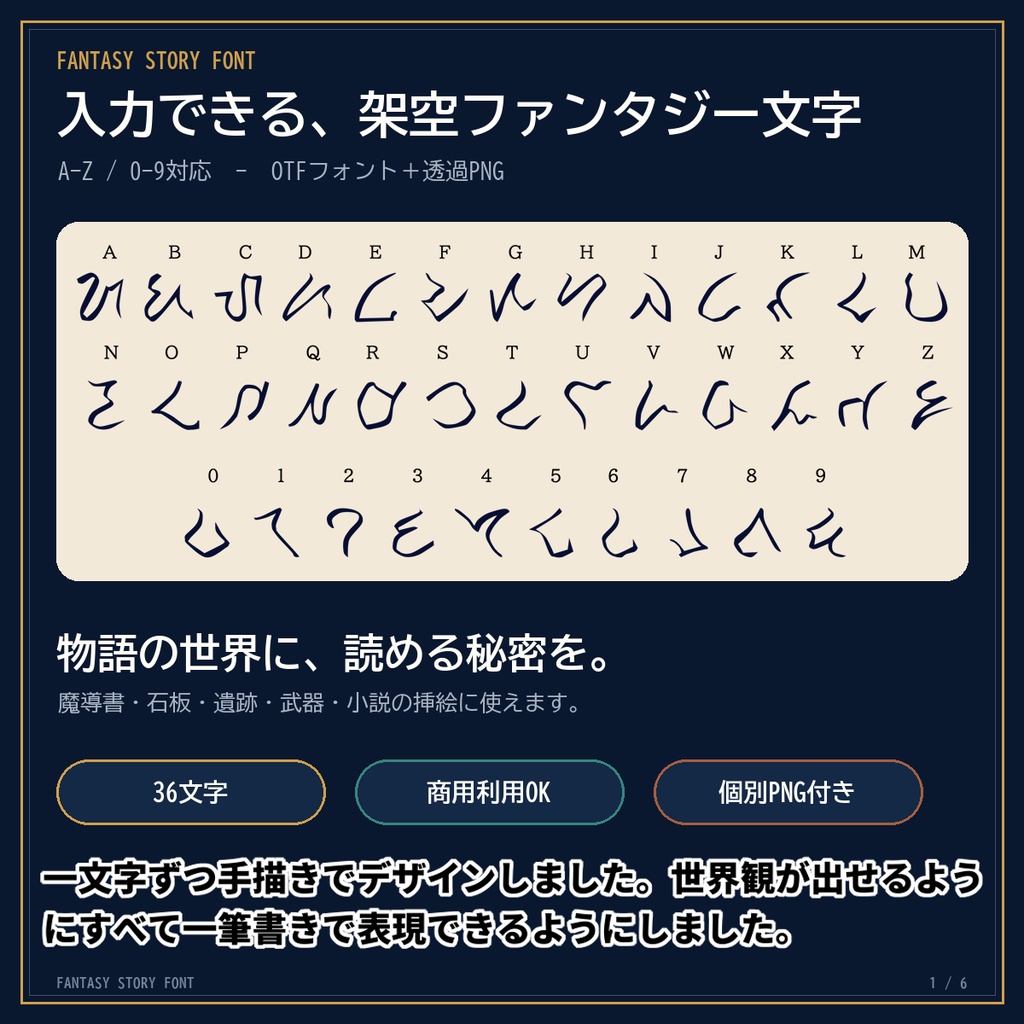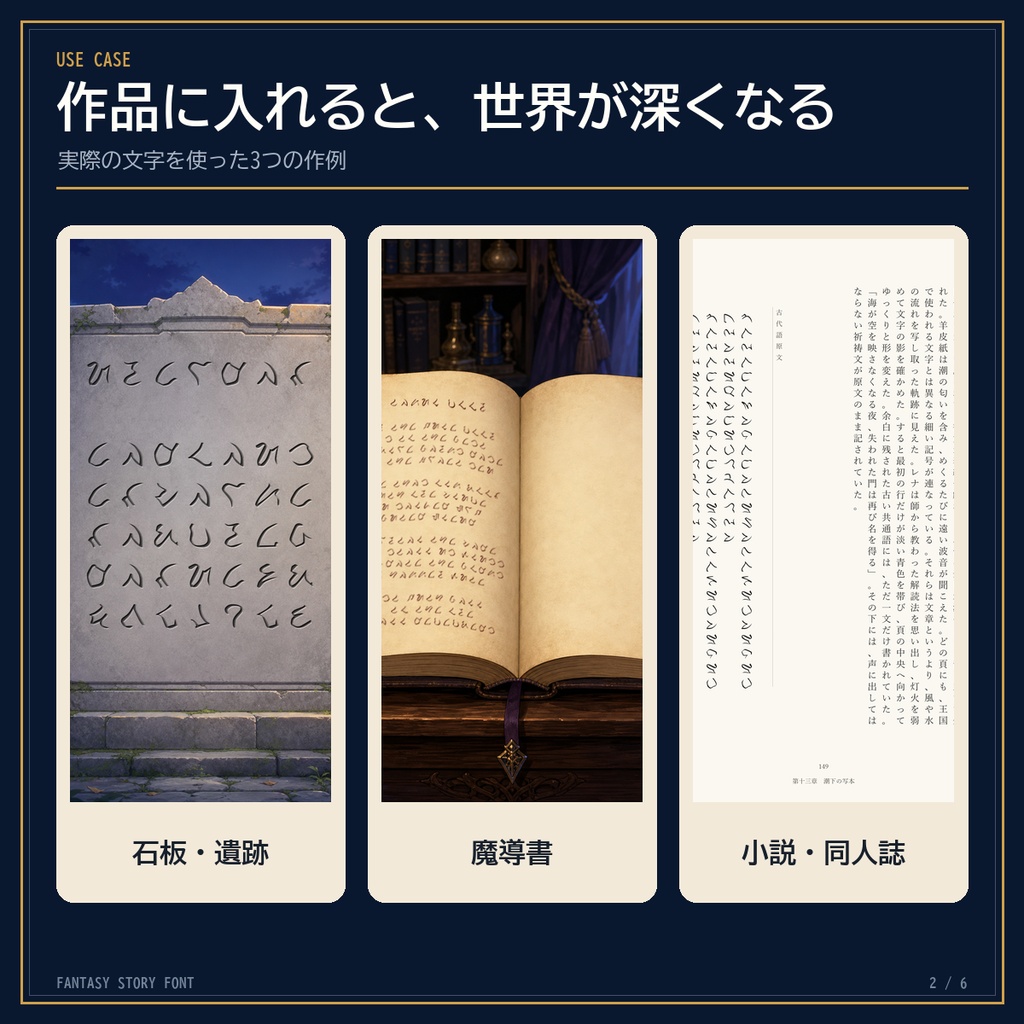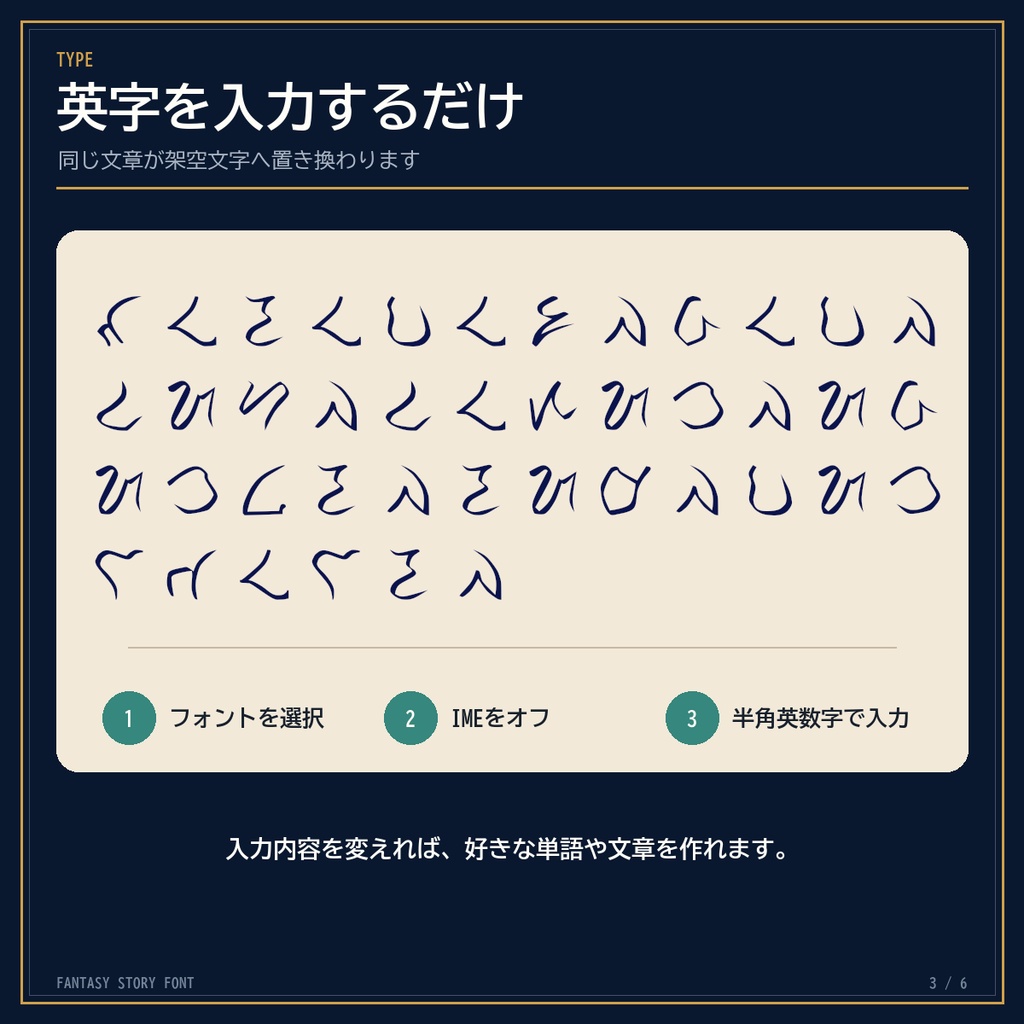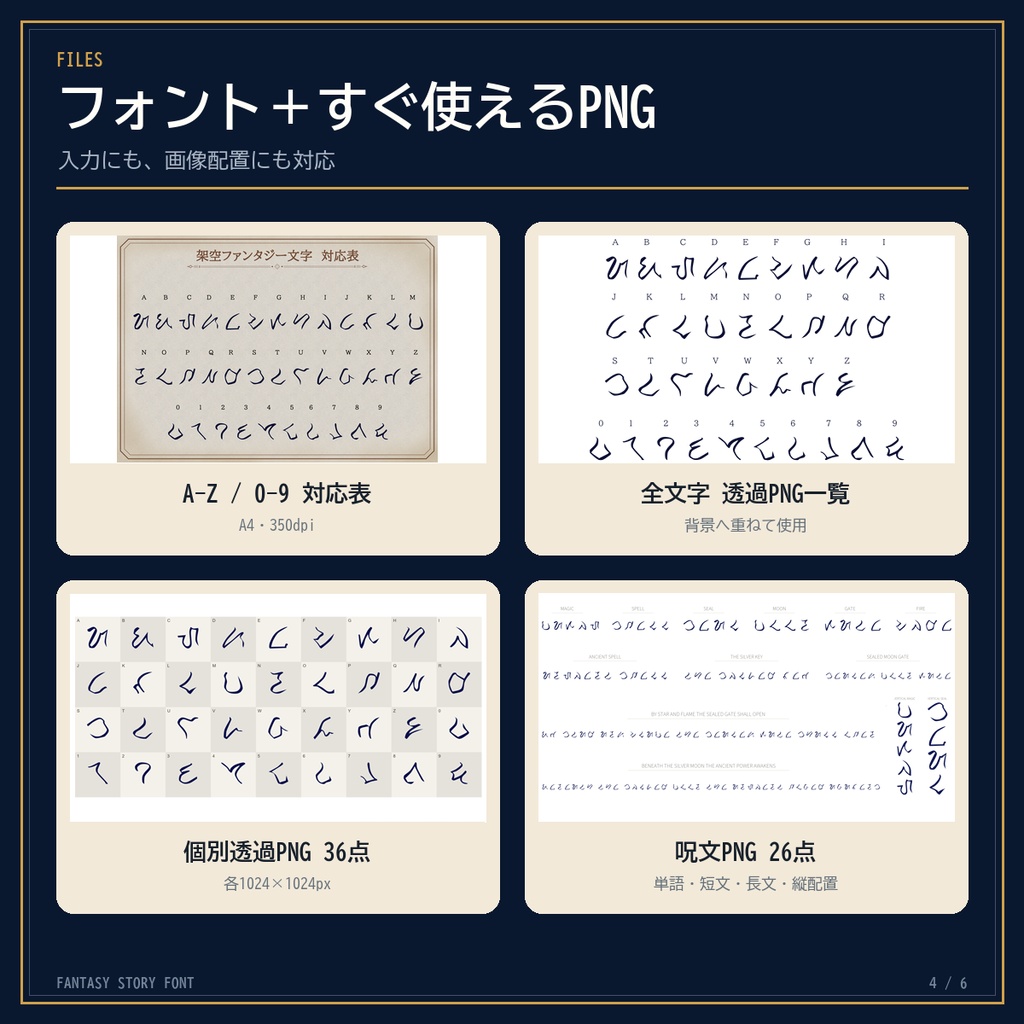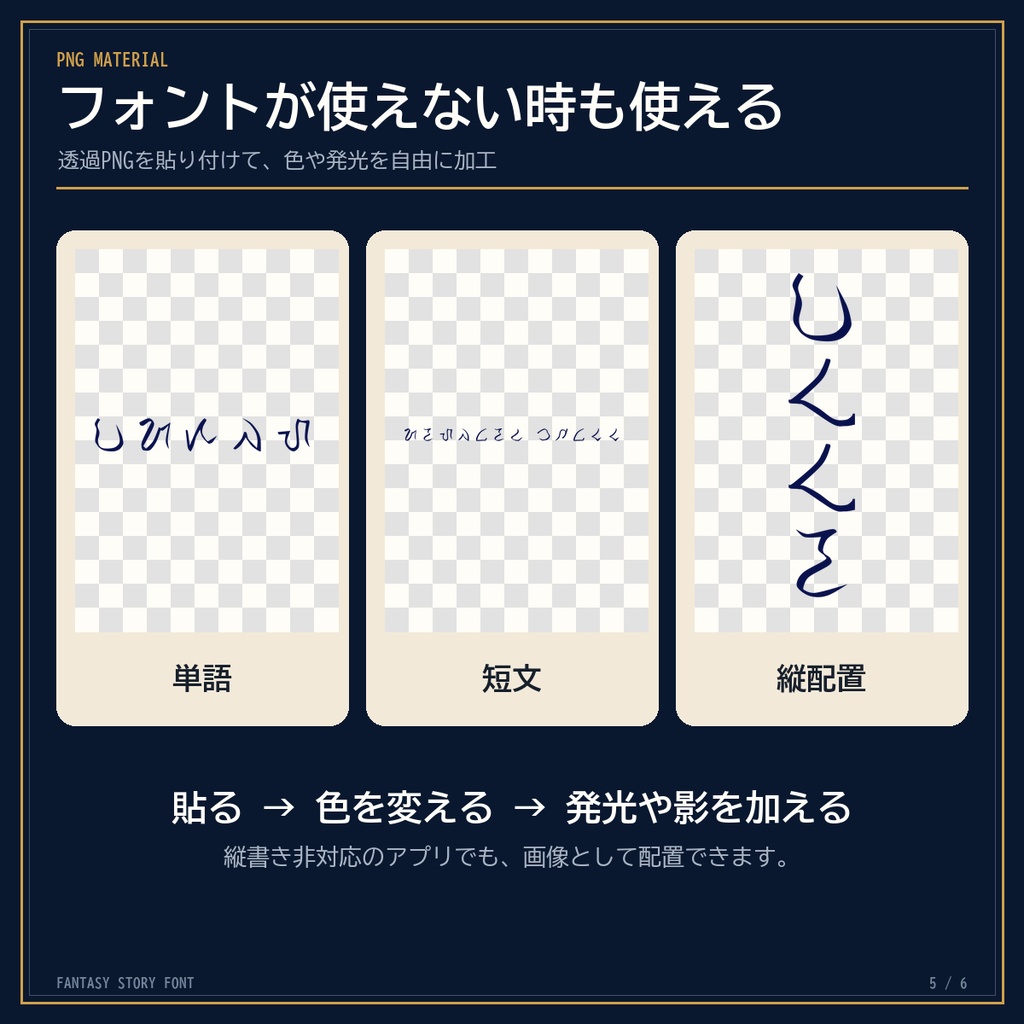
Fantasy Story Font|入力できる架空文字フォント
ファンタジー世界に使える架空文字を、キーボードから簡単に入力できるファンタジーフォントです。 半角英数字 A-Z / a-z / 0-9 を架空文字として入力できます。 ※大文字・小文字は同じ字形で表示されます。 【無料お試し版について】 無料お試し版には、一部の文字・数字の個別透過PNGと、作成済み文字PNGを収録しています。 一文字ずつデザインして、一貫性を持たせるためすべて一筆書き出来る文字にしました。 半角英数字 A-Z / a-z / 0-9 を入力するだけで、オリジナルの架空ファンタジー文字へ置き換わります。 イラスト、小説、同人誌、漫画、動画、ゲーム、TRPG資料など、世界観を演出したい場面にご利用いただけます。 フォント入力だけでなく、全文字の個別透過PNGと、作品へそのまま貼れる呪文PNGも収録しています。 フォントを使えないアプリや、縦配置を作りたい場合にもお使いいただけます。 【こんな場面におすすめ】 ・魔導書や古文書の文章 ・遺跡、石碑、石板、壁の刻印 ・呪文、暗号、封印、秘密の手紙 ・小説や同人誌の章扉、挿絵、引用文 ・ゲームやTRPGの地図、アイテム、資料 ・AIイラスト完成後の文字演出 AIイラストへ後から加えることで、生成時に起こりやすい文字化けを避けながら、ファンタジーらしい情報を追加できます。 【フォントについて】 フォント名:Fantasy Story Font ファイル形式:OpenType(OTF) 入力文字:半角英数字 A-Z / a-z / 0-9 (文字サイズは字体は同じものにまります) 入力方向:横書き専用 IMEをオフにして、半角英数字で入力してください。 縦に配置する場合は、付属の個別透過PNGまたは縦配置PNGをご利用ください。 【収録内容】 はじめに テキストが文字化け等する場合はこちらをお読みください 1.フォント ・FantasyStoryFont-Regular.otf 1点 2.文字対応表 ・A-Z、0-9対応表 A4横PNG 1点 ・4093×2894px/350dpi 3.透過PNG一覧 ・A-Z、0-9一覧 A4横PNG 1点 ・4093×2894px/350dpi 4.個別透過PNG ・A.png-Z.png 26点 ・0.png-9.png 10点 ・各1024×1024px 5.完成済み呪文PNG ・単語 12点 ・短文 6点 ・長文 2点 ・縦配置 6点 6.ガイド・利用規約 ・使用例 ・インストールガイド ・利用規約 フォント以外のPNG素材は合計64点です。 すべての商品データをZIP形式でまとめています。 【動作確認】 Windows環境で、以下のアプリからA-Zと0-9の入力を確認しています。 ・メモ帳 ・GIMP ・SAI2 ・CLIP STUDIO PAINT macOSでも利用できるOTF形式ですが、制作者はMacを所有していないため実機確認は行っていません。 OS、アプリ、アップデートなどにより、表示や操作が異なる場合があります。 【ご利用について】 ・個人利用、商用利用可能 ・色変更、変形、発光、ぼかしなどの加工可能 ・使用報告、クレジット表記は任意 ・AI生成イラストへの後付け利用可能 禁止事項 ・フォント、PNG、対応表、説明書などの転載、譲渡、共有、販売、再配布 ・加工した素材を、フォントや素材集として販売または配布すること ・本商品を自分で制作したものと偽ること ・フォントやPNGをAI学習用データとして提供、配布、販売すること ・法令、公序良俗に反する目的での使用 詳しくは商品に同梱している「利用規約.txt」をご確認ください。 【ご注意】 ・ダウンロード後、ZIPファイルを解凍してからご利用ください。 ・フォントをインストールした後は、使用するアプリを一度終了して再起動してください。 ・本商品はデジタルデータです。紙の商品や物品の発送はありません。 ・すべての環境での動作を保証するものではありません。 【お問い合わせ】 2D WALKER by BLUE お問い合わせはBOOTHショップのメッセージ機能からお願いいたします。